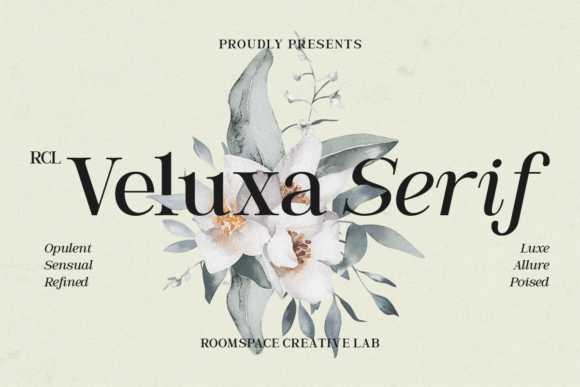
Veluxa Serif
Veluxa Serif: A Fonte que Eleva o Luxo Moderno
Se você procura a tipografia perfeita para transmitir prestígio, elegância feminina e um toque de sensualidade refinada, a Veluxa Serif da Roomspace Creative Lab é a escolha ideal. Criada como uma aula‑mestre de luxo contemporâneo, esta fonte combina traços finos com serifa pontiaguda que lembram agulhas, resultando em um visual “Luxe” e “Allure” que se destaca em qualquer aplicação de alto padrão.
- Altura-x generosa: garante ótima legibilidade mesmo em tamanhos pequenos.
- Proporções sofisticadas: as serifas delicadas criam um contraste elegante entre leveza e força.
- Ligaduras refinadas: adicionam um toque artesanal a logos e headlines.
- Versatilidade de layout: funciona melhor em espaços com bastante white space, permitindo que os detalhes intrincados respiram.
- Compatibilidade visual: combina perfeitamente com ilustrações botânicas ou fundos em aquarela suave, reforçando a identidade visual “opulenta” e “poised”.
Por que a Veluxa Serif se destaca no mercado?
Além de sua estética luxuosa, a Veluxa Serif oferece proporções equilibradas que evitam a fadiga visual, tornando‑a ideal para materiais que exigem leitura prolongada, como revistas e menus. Sua presença marcante em branding de moda e embalagens de skincare boutique cria uma conexão emocional instantânea com o público-alvo, reforçando a percepção de exclusividade.
Casos de Uso Ideais
- Logotipos de marcas de moda e beleza
- Embalagens de cosméticos premium
- Identidade visual de cafés boutique
- Layouts de revistas de luxo e convites sofisticados
- Posts de redes sociais que buscam destaque visual
- Materiais de marketing e campanhas publicitárias de alto padrão
Como aplicar a Veluxa Serif para maximizar seu impacto
1. Reserve espaço em branco: use margens amplas para que as serifas e ligaduras respirem.
2. Combine com cores neutras ou pastel: tons suaves realçam a delicadeza da fonte sem competir com ela.
3. Integre ilustrações botânicas ou texturas de aquarela: esses elementos criam um contraste visual que enfatiza a “luxúria” da tipografia.
4. Use as ligaduras em headlines: elas conferem um toque sob medida que diferencia sua marca da concorrência.
A Veluxa Serif não é apenas uma fonte; é um instrumento de comunicação de alto nível que transforma qualquer projeto em uma experiência de luxo refinado. Seja para criar um logotipo impactante, uma embalagem de beleza irresistível ou um convite elegante, esta tipografia entrega prestígio, elegância e atração sensual em cada caractere. Não perca a oportunidade de elevar sua marca ao próximo patamar com a Veluxa Serif.